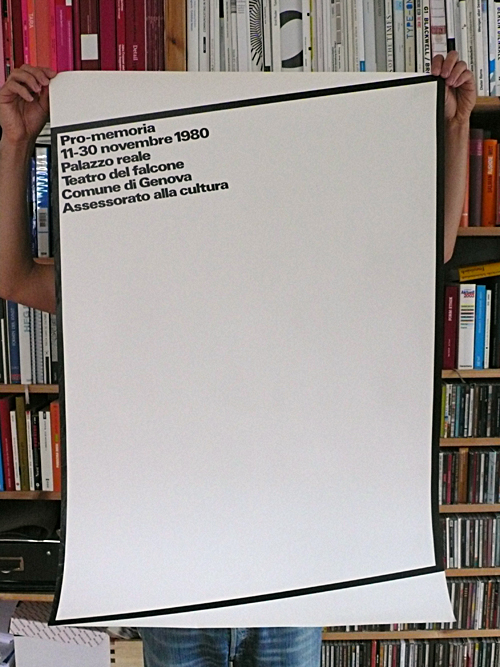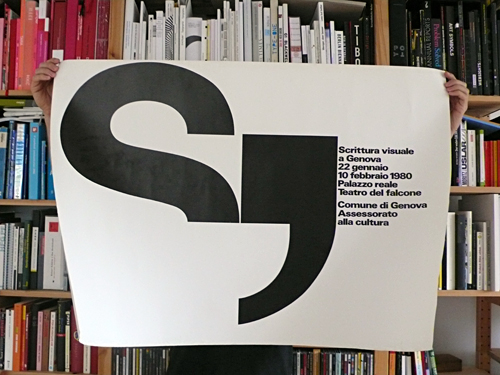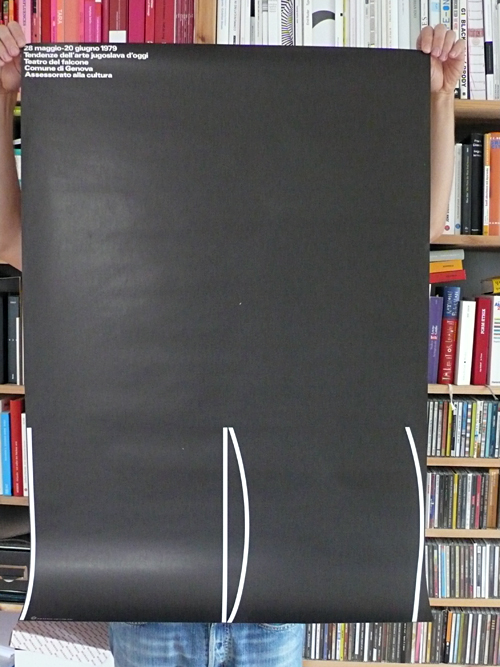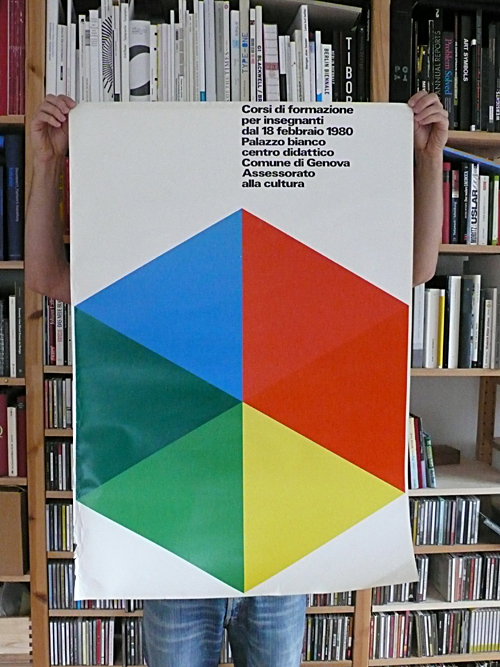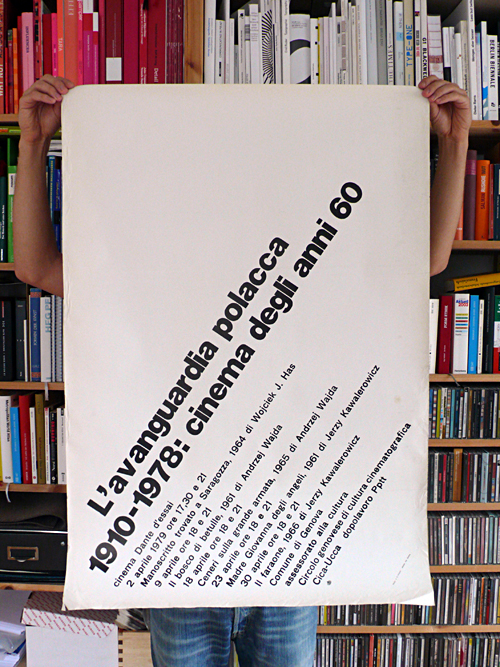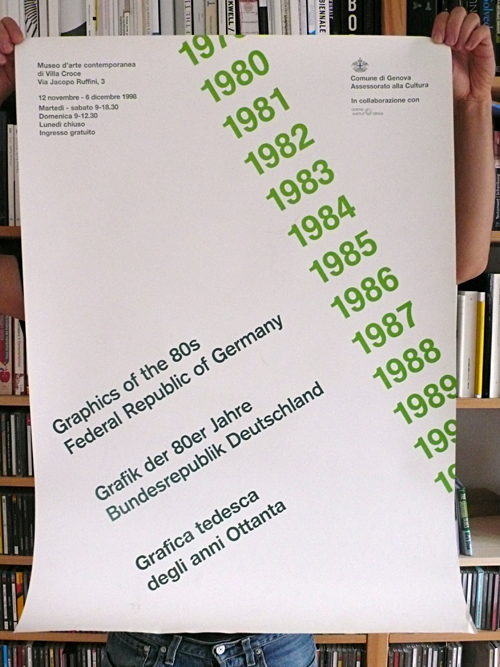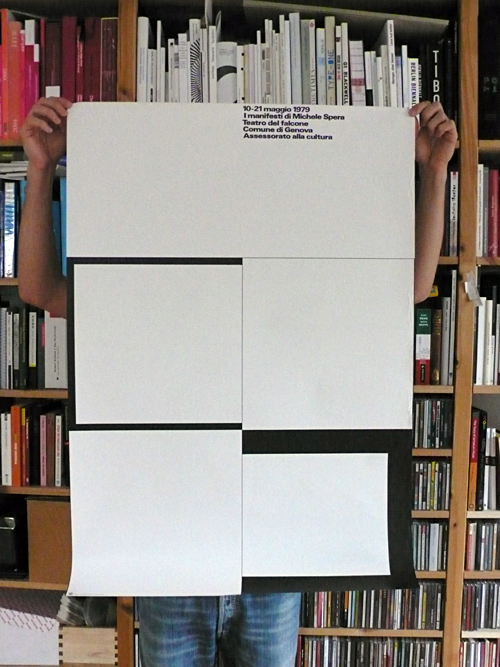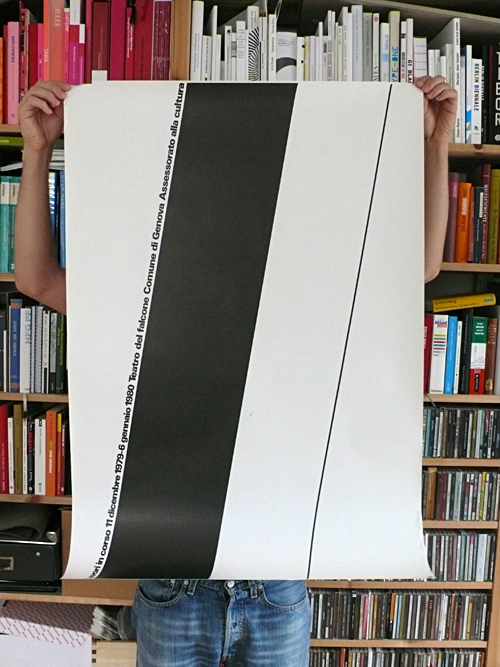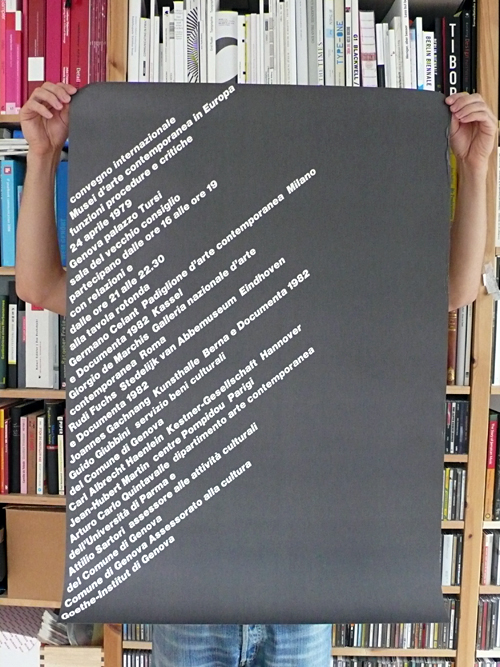
tipografia italiana
Bei einem Besuch in Genua durfte ich im Plakatarchiv einer traditionsreichen Kulturinstitution der Stadt, der Villa Croce, wühlen. Dabei fanden sich so manche kleine Zeitzeugen der typografischen Kultur aus der Zeit Ende 70er, Anfang 80er.
Inwieweit dies für andere Länder Europas repräsentativ war oder ob Italien in diesem Punkt ca. 10–15 Jahre hinter Deutschland und der Schweiz lag, sei mal dahin- und somit zur Diskussion gestellt.
Visuelle Schrift in Genua
Post-its (oder: Merkzettel)
Formationskurse für Erwachsene
Polnische Avantgarde
Deutsche Grafik in der 80ern
Gesammelte Poster von Michele Spere
In Abeit (oder: Baustelle)
Europäische Museen im Gespräch
Moderne jugoslavische Kunst